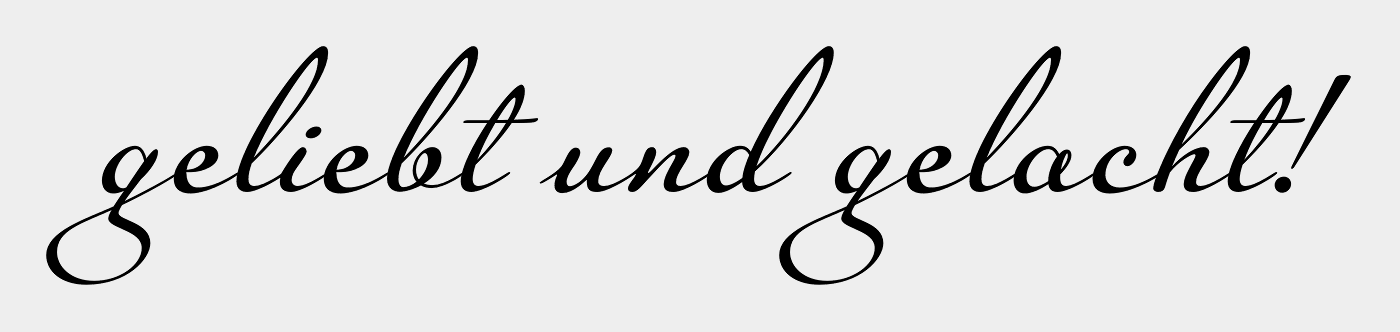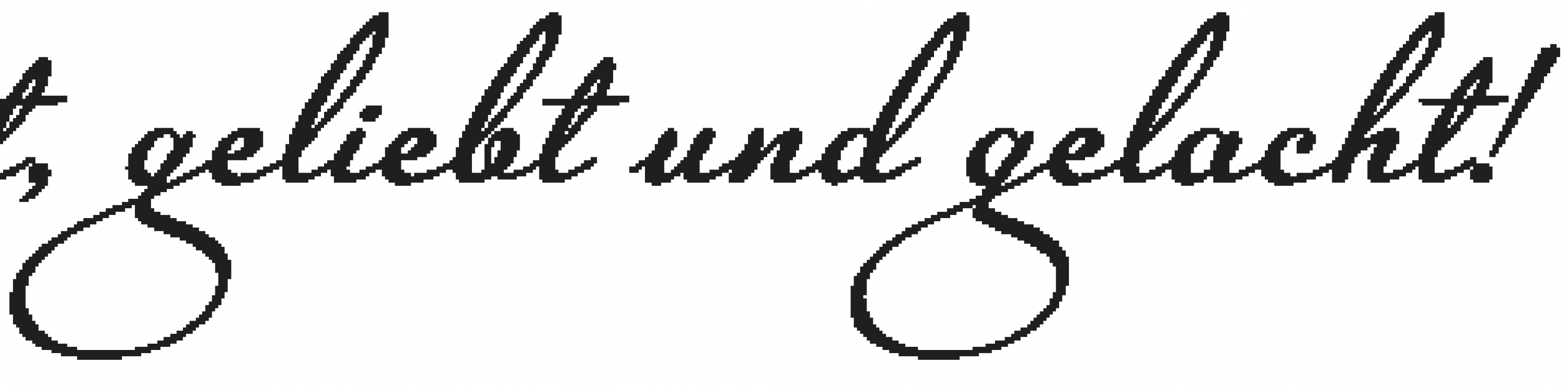
Suche Kalligraphie-Schriftart
kennt jemand die Schrift von "geliebt und gelacht" der beigefügten Beispielgrafik?
Oder handelt es sich vielleicht um eine Eigenkreation?
Die Auflösung ist leider nicht so gut.
... künstlich verfettet, ...
Ein Font gras wird wohl die Schriftschützer auf den Plan bringen ;-)
Entsteht nicht auch beim Buchdruck eine leichte Verfettung der Schrift, weil sich beim Einfärben die Druckfarbe ja auch ein wenig um die Kante der Lettern herum legt, und das beim Druck dann eben auch aufs Papier kommt?
Die Schrift-Verfettung beim Hochdruck entsteht durch den Quetschrand.
Die Farbe wird beim Druck mehr oder weniger über den Rand des Schriftbildes der Letter gequetsch. Dadurch entsteht auch ein minimaler Abstand zum Schriftbild und der weggequetschten Farbe.
Der Grad der Schrift-Verfettung hängt vom Können des Druckers ab und sicher auch von der Qualität der Bleilettern. Lettern, die schon oft verwendet wurden, sind auch etwas fetter und wirken abgerundet. Da beginnt die schwierige Arbeit des Druckers, der nun ein bestmögliches Schriftbild im Druck erzeugen soll.
Es gibt Werke, da kann man nur mit der Lupe den „Quetschrand“, der die Verfettung ausmacht, erkennen. Ich kann mich aber auch selbst daran erinnern, abgebrochene Lettern bei der Revision ausgetauscht zu haben. Da war wohl der Druck nicht richtig eingestellt.
Dank einer mehr als leichten Verfettung durch den Druck ist eines meiner in der Stempel Garamond gesetzten Lieblingsbücher überhaupt lesbar. Sonst wäre die Schrift nämlich viel zu spillerig. Und damit stellt sich die Frage, ob die Outlines einer Schrift in Bezug auf ihre Stärke Quetschränder berücksichtigen sollten oder nicht. So rein instinktiv würde ich sagen, dass sie sie nicht berücksichtigen sollten. Denn ideal wäre es, wenn sie beim Druck genau so abgebildet werden würden, wie sie gestaltet wurden. Bleidruck und andere Techniken, bei denen die Schriften nicht als Computer-Fonts vorliegen, klammere ich mal aus.
Und hier denke ich, dass die alten Meister der Schriftgestalter und Stempelschneiderzunft diesen Dickenzuwachs durch die Quetschränder sehr wohl berücksichtigten. Schließlich schnitten sie ja ausschließlich für den Buchdruck.
Und jetzt wird digitalisiert... Hier gibt es mit den großen Schriftenhäusern eben die Erben der alten Bleigießer, die dann in ihren Schatzkammern die echten Originale aus der Hand der großen Schriftgestalter besitzen. Und diese lassen sich dann auch präzise, ja teils über präzise digitalisieren. Das bedeutet, exakt auf der Kontur der originalen Stahl-Stempel.
Und dann gibt es die kleinen Digital-Foundries ohne diese Schätze. Denen bleibt nichts anderes übrig, alte Drucke als Vorlage zu nehmen, diese kräftig vergrößert als Digitalisiervorlage zu nutzen, zwangsläufig dann mit diesen Quetschrand   und hier nur die unakuraten Konturen durch Fasern und Papierschattierungen heraus korrigieren können. Das Ergebnis ist dann eben eine Schrift, nach den fertigen Konturen des gedruckten Werkes.
Das Problem: Diese Schriften bekommen dann genau die falschen in die Hände: Die Profigestalter kaufen sich die teuren Original-Lizenzen, mit den Schriften nach den Entwürfen und Originalstempel - und das wird dann mit modernsten Druckmaschinen aufs Papier gebracht, bei der dann nichts über den Rand der Vektoren hinweg druckt, und man regt sich auf, dass die Digitalisierung viel zu spillerig geraten ist, dass der Text kaum noch vernünftig lesbar ist.
Und dann sind da sind diese Otto Normaluser, welche sich die 10000 Fonts für 13,95 CD gekauft haben, und da sind dann die Billigdigitalisierungen mach den Drucken drauf, die eigentlich ja diesen Quetschrand-Zuwachs berücksichtigen, und ausgerechnet die drucken das dann mit ihren Tintenpissern auf dem saugfähigen 3,5/Ries Billigpapier aus, und bekommen zu den digitalisierten Quetschrändern noch reichlich Saugränder hinzu, und die Schrift läuft fast zu, so sehr verfettet sie sich.
Also Moment, so wie du das darstellst, glaub ich das nicht. Der Idealfall wäre doch der, dass die Outlines einer Schrift den Quetschrand nur soweit berücksichtigen, wie er unter idealen Druckbedingungen auftritt. Und ideal wäre kein Quetschrand oder ein standardisierter Quetschrand. Warum? Weil weniger Absprachen zwischen den an der Produktion eines Druckwerks Beteiligten notwendig sind, wenn alles genormt ist. Und beim Bleisatz wird was anderes ideal sein als beim Offsetdruck. Was die großen Foundries bei der Digitalisierung eben oft nicht gemacht zu haben scheinen, ist, die Fonts auf Basis derjenigen Originale zu digitalisieren, die für Lesegrade optimiert waren.
Naja, ich find schon, dass das eben noch etwas anders klang. Typetogether, Lazydogs (namentlich die Fabiol), Feliciano Type Foundry, German Type Foundry – alles im Vergleich zu Monotype kleine Foundries, die aber erstklassige Fonts produzieren. Hier lesen ja auch Leute mit, die nach Schriften suchen und die kleinen Foundries gar nicht kennen. Und denen würde ich halt sagen, dass ihr Geld möglicherweise besser bei einer dieser relativ kleinen Foundries aufgehoben ist, als es Monotype in den Rachen zu stecken. Von Berthold ganz zu schweigen. Nach der Sache mit der absurden EULA ist Berthold bei mir wirklich unten durch. Ist ja nicht so, als gäbe es da keine guten Alternativen. Ich hatte vor ein paar Jahren die Ehre, mich um das Hinting der Fonts eines mexikanischen Typedesigners kümmern zu dürfen. Der hatte, soweit ich mich erinnere, auch keinen Zugriff auf Original-Zeichnungen. Aber seine Schriften sind trotzdem besser als das Meiste, das ich in den letzten Jahren von Monotype oder Linotype gesehen habe. Und der hatte sein Studium noch nicht mal beendet, profitierte also auch nicht von Erfahrungen, die er im Laufe eines langen Berufslebens gesammelt hat. Jedenfalls gibt es erfreulich viele neue Meister, die den alten durchaus ebenbürtig sind. Übrigens auch so ein Thema: Es gibt verhältnismäßig viele gute lateinamerikanische Schriftgestalter.